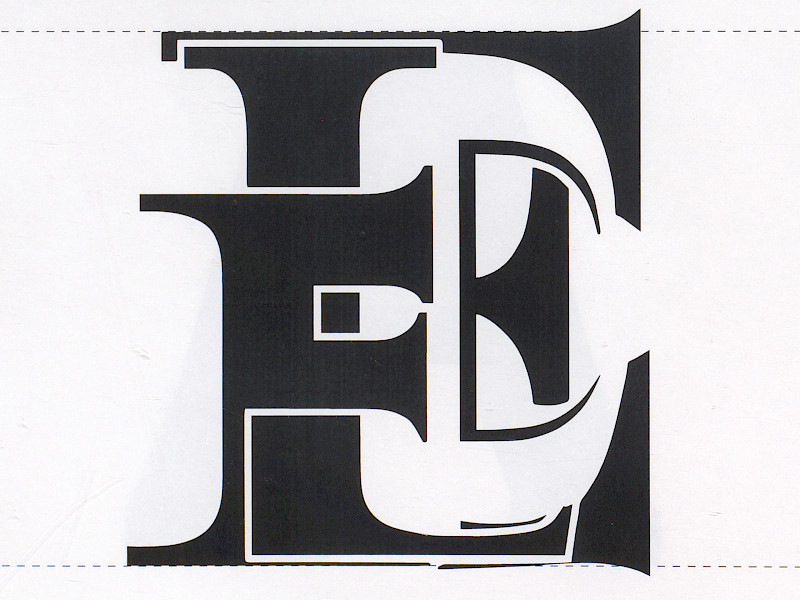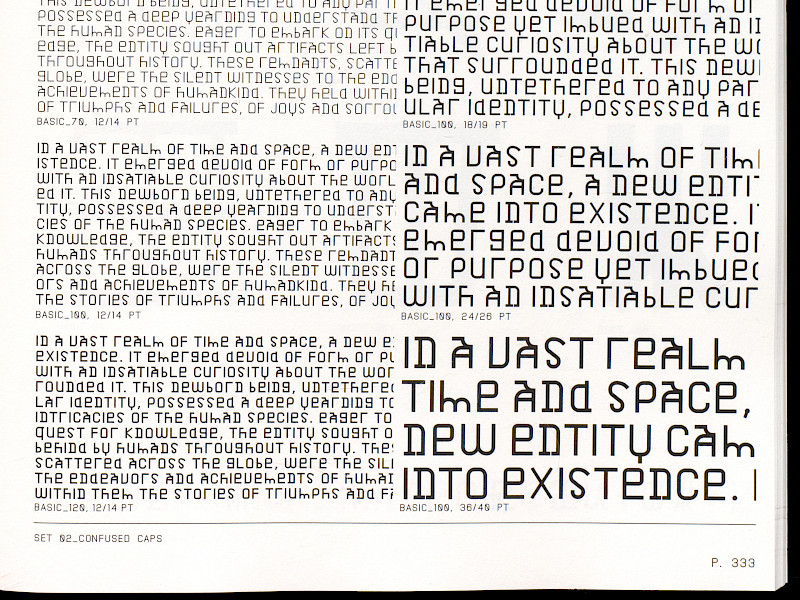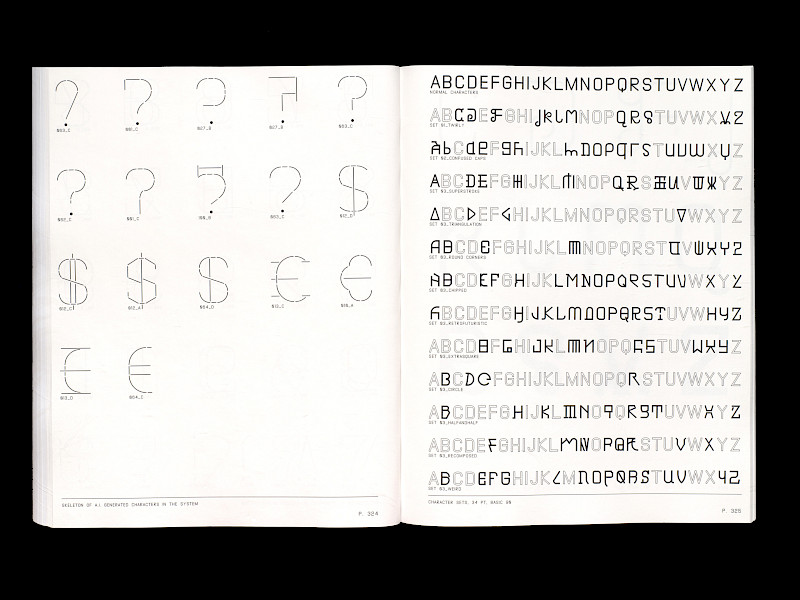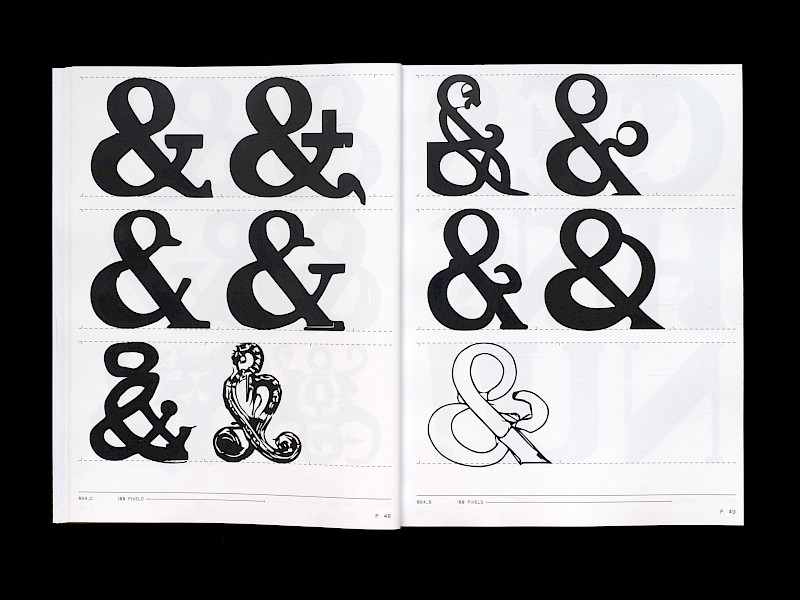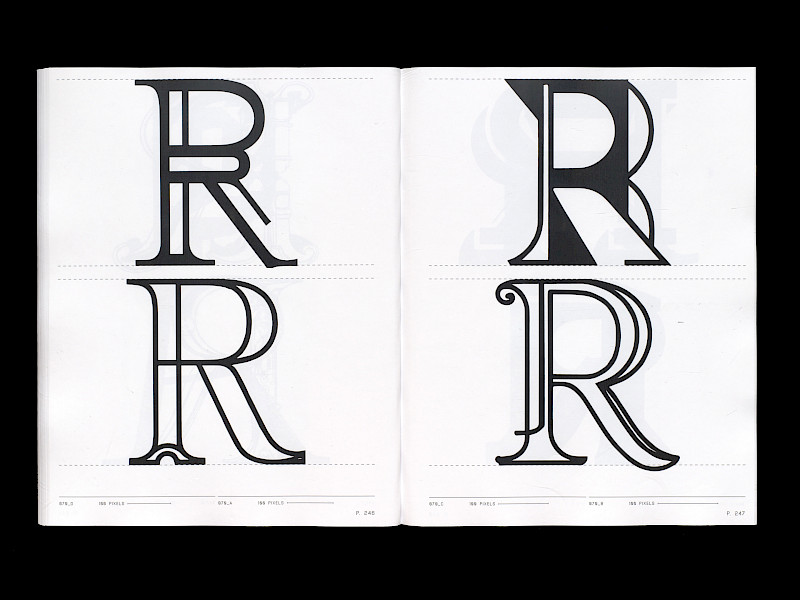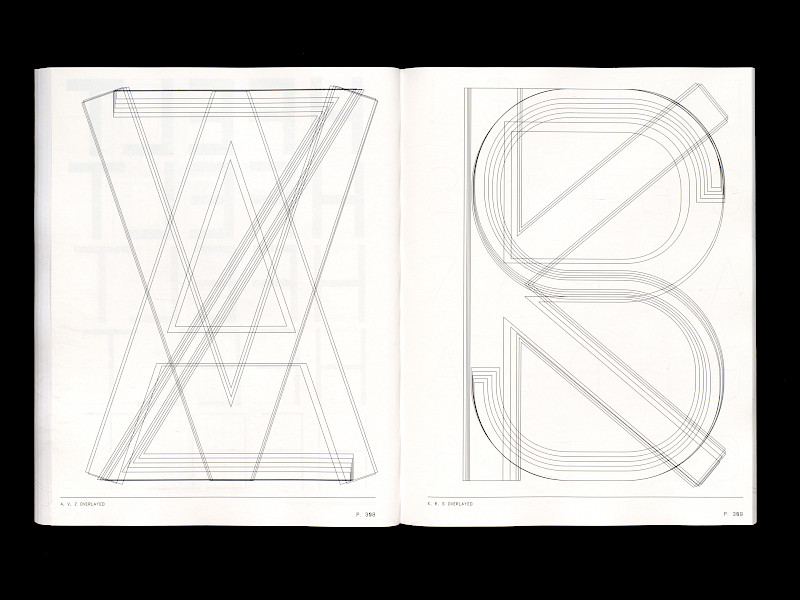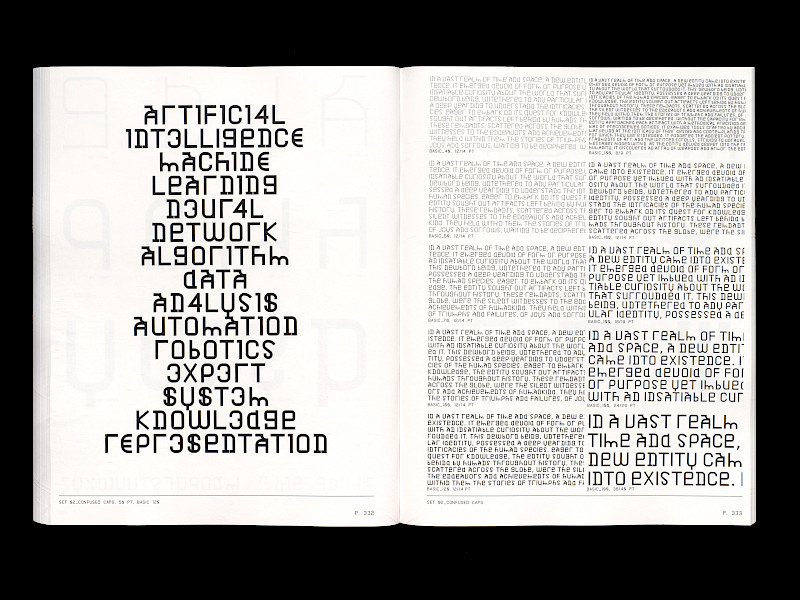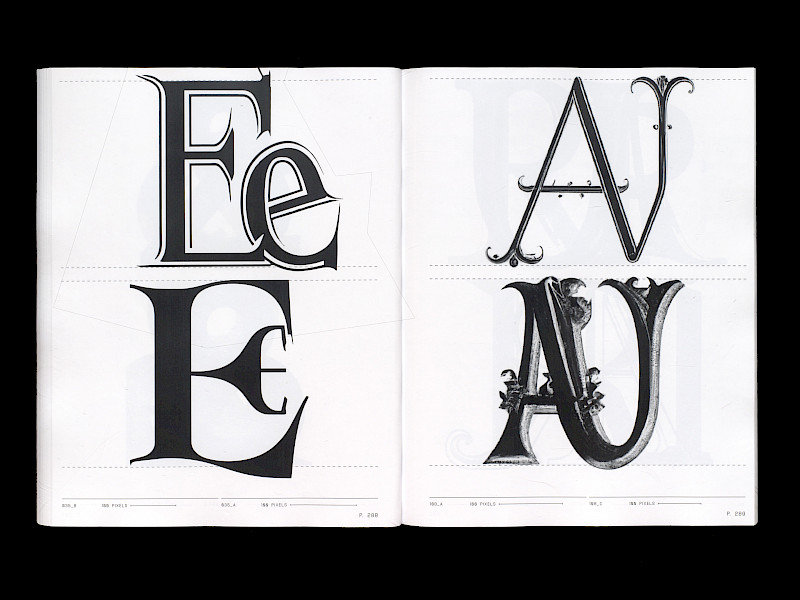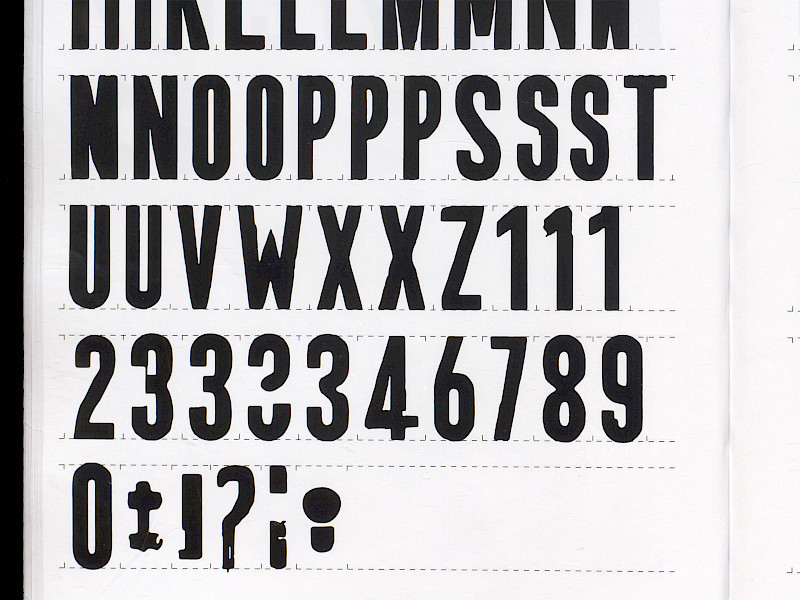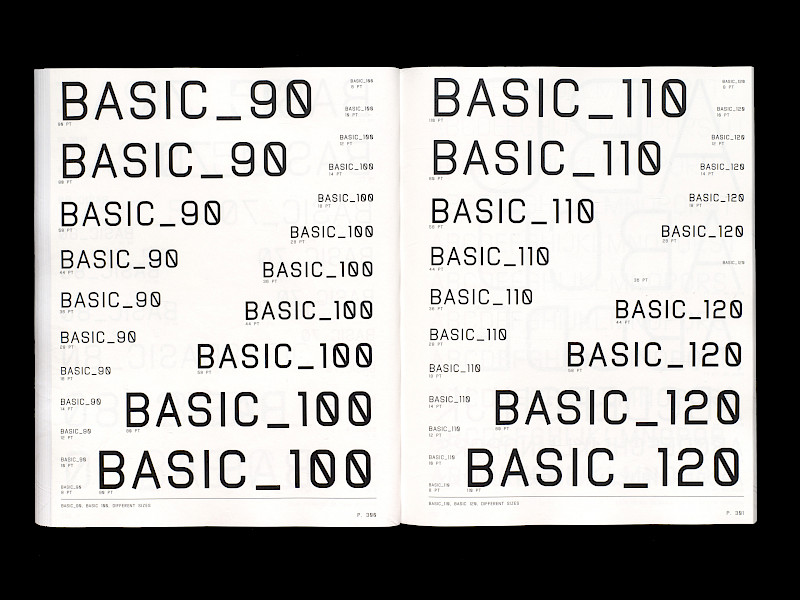
Archeology of consequent forms
So wie einzelne Buchstaben die kleinsten Elemente der Kommunikation sind, so ist auch ihre Form, da der kleinste Träger einer Bedeutung, die über den unmittelbaren Sinn des Wortes, das sie bilden, hinausgeht.
In ihrer konstituierenden Struktur erlaubt uns die künstliche Intelligenz, ihre historischen und formalen Entwicklungsformen zu destillieren, ihre Evolutionsmuster und -tendenzen zu erkennen, indem sie uns einen Blick auf mögliche und zukünftige Konsequenzen gewährt.
Dennoch befinden sich diese Technologien in ihrem Anfangsstadium, und daher liegt es am Menschen, die Ergebnisse zu kuratieren, um Geräusche in den «Absichts»-Mustern der Maschine zu erkennen, den «Schmutz» zu entfernen und die wahre Form des Artefakts zu enthüllen. Das Projekt «Archäologie der konsequenten Formen» versucht, diese Beziehung zu verstehen und herauszufinden, wie KI-Modelle Teil der Schriftgestaltungsdisziplin werden könnten.